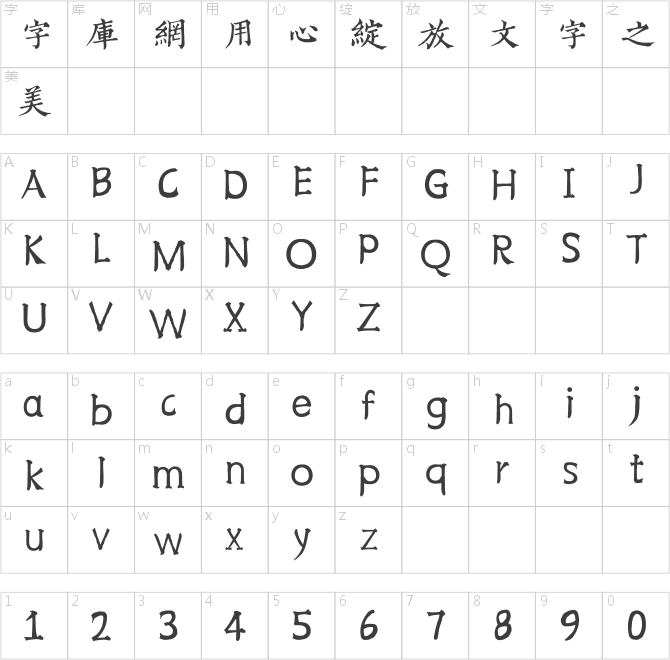
(清)存素堂刻本繁體 詳情頁
本字體以清代存素堂刻本為藍(lán)本運用軟件制作而成,筆畫流暢飛揚,結(jié)體左緊右松,開合對比強烈,進(jìn)一步強化了動感。整套字體有如一氣呵成,行筆迅捷華麗,其個性浪漫灑脫,適用于現(xiàn)代詩歌、短文的排版,以及文化、商業(yè)類品牌的廣告語設(shè)計。